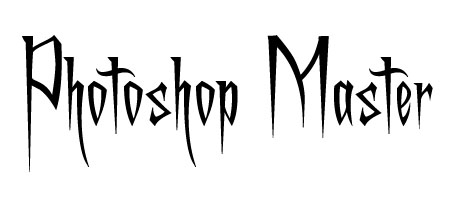
да кст...очень напоминает Поттера)
Просто офигенно!)
Гарри Поттер :D
Клевый шрифт)
Где-то я это уже видел... всмысле шрифт этот... тут на сайте... повтор что ли...
Не знаю короче но шрифт красивый)
напоминает Гарри Поттера))
очень даже нечего!
Супер !!! Побольше бы подобных !!!